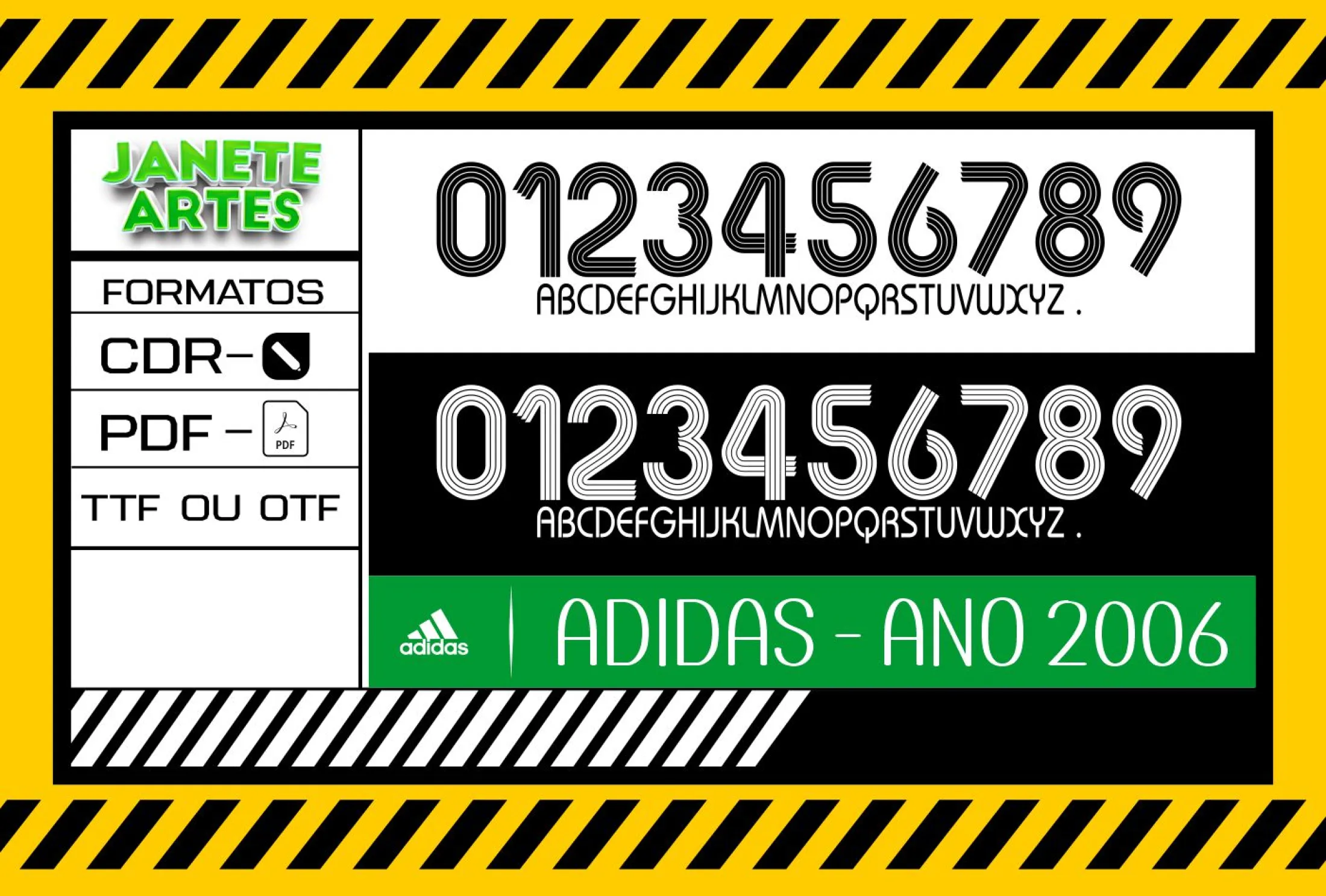
Fonte de Time Tipografia Adidas 2006
Fonte de Time Tipografia Adidas 2006 é um arquivo digital para personalizar camisetas com estilo esportivo e profissional, perfeito para fãs do futebol que querem uma camisa exclusiva.
• Alta qualidade no traço da tipografia